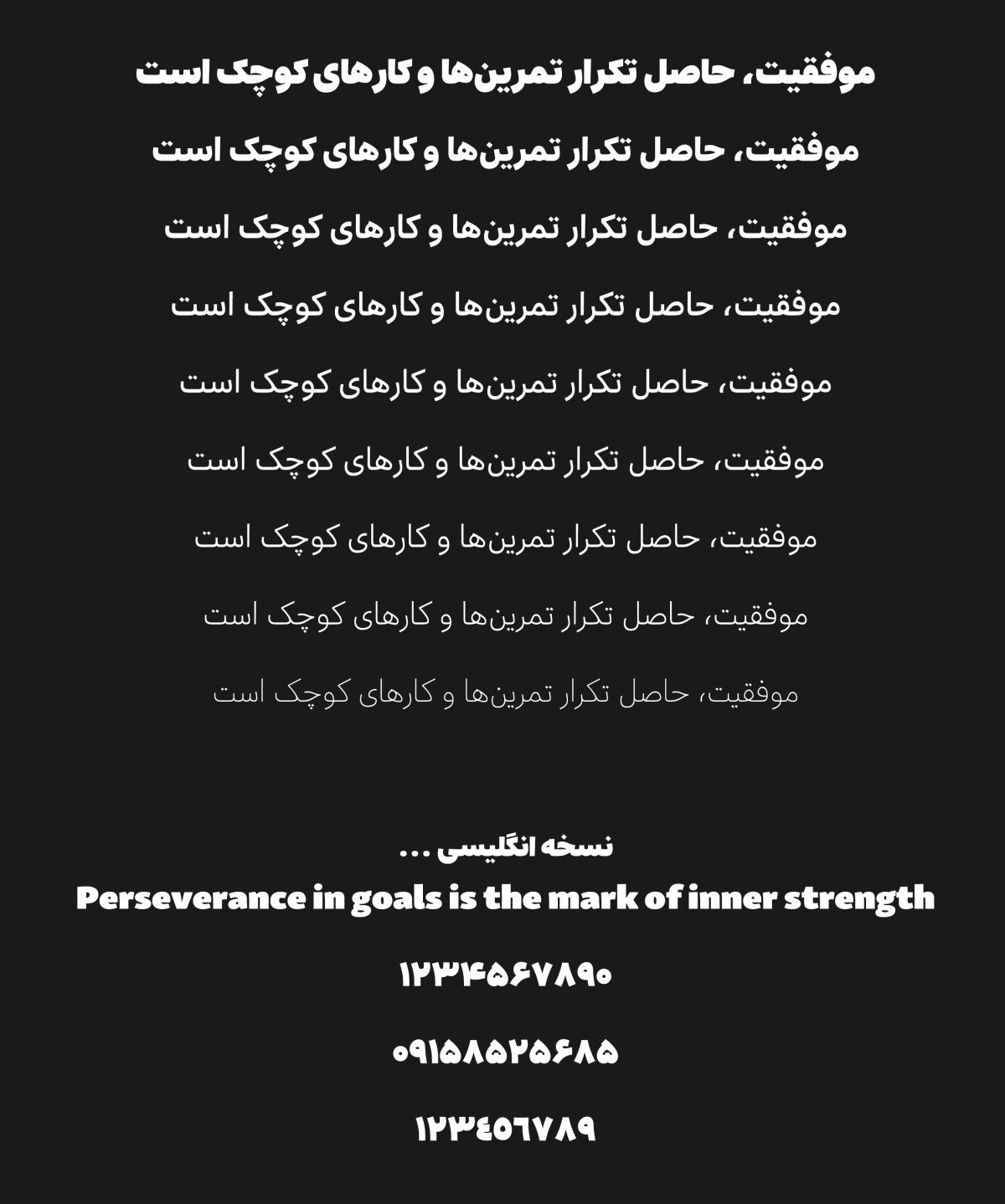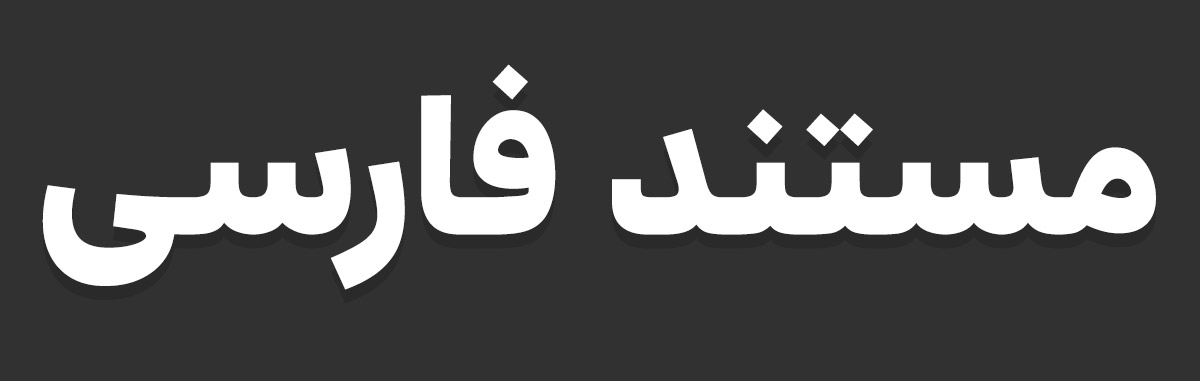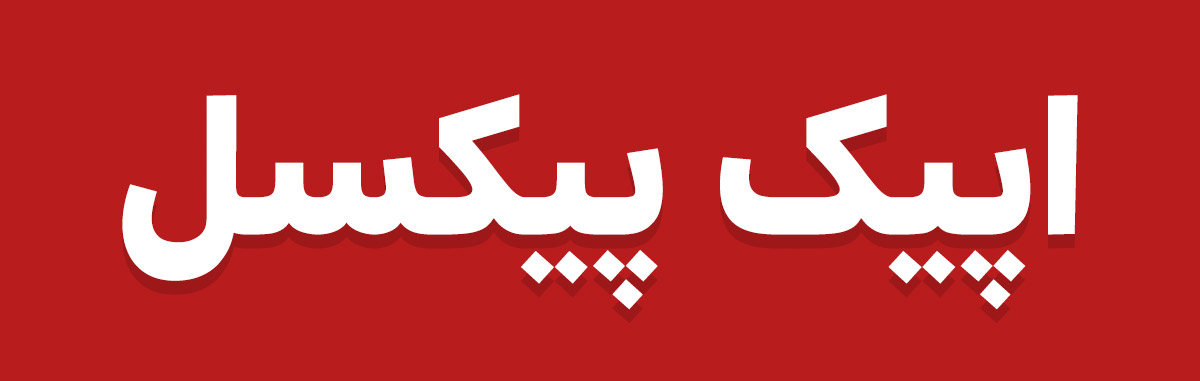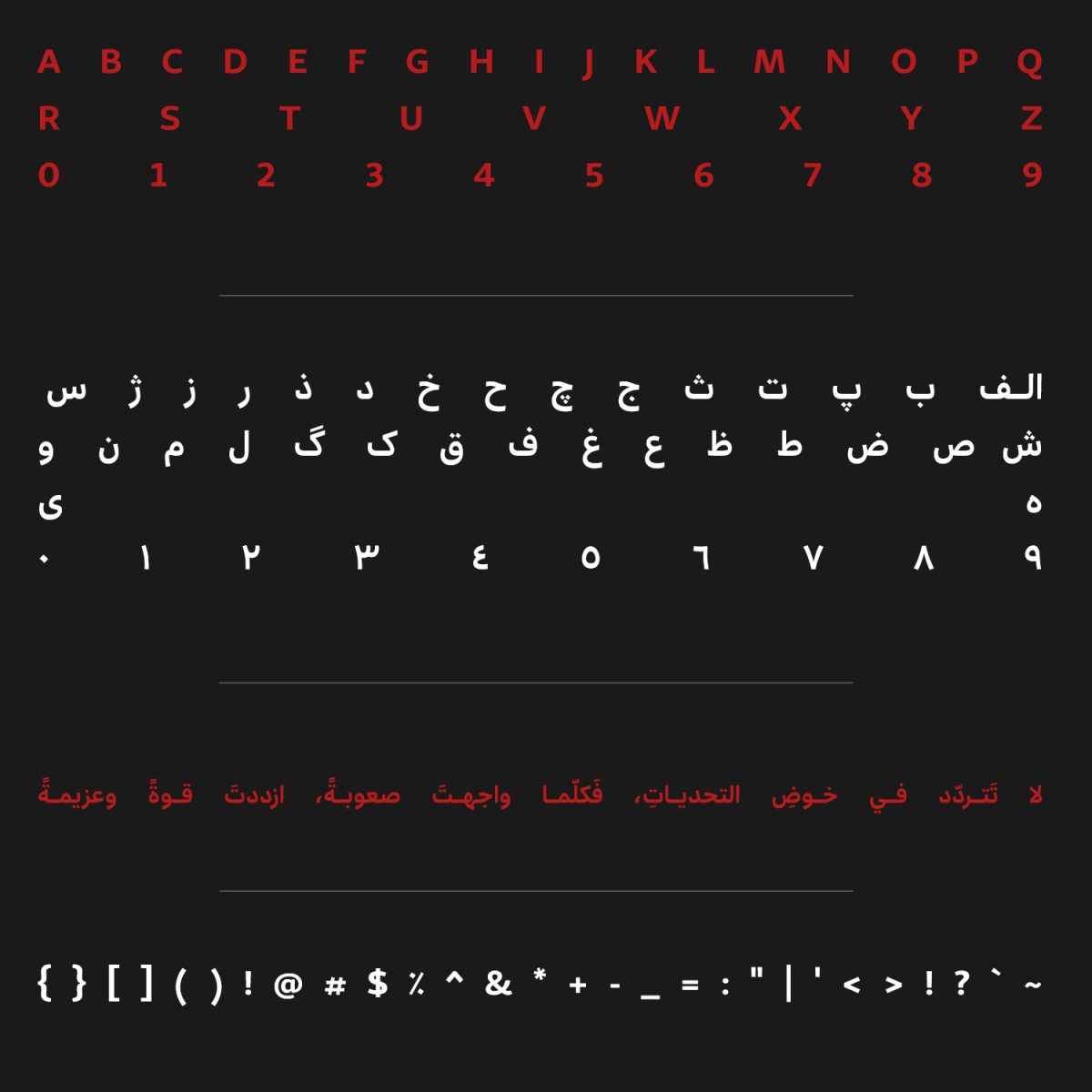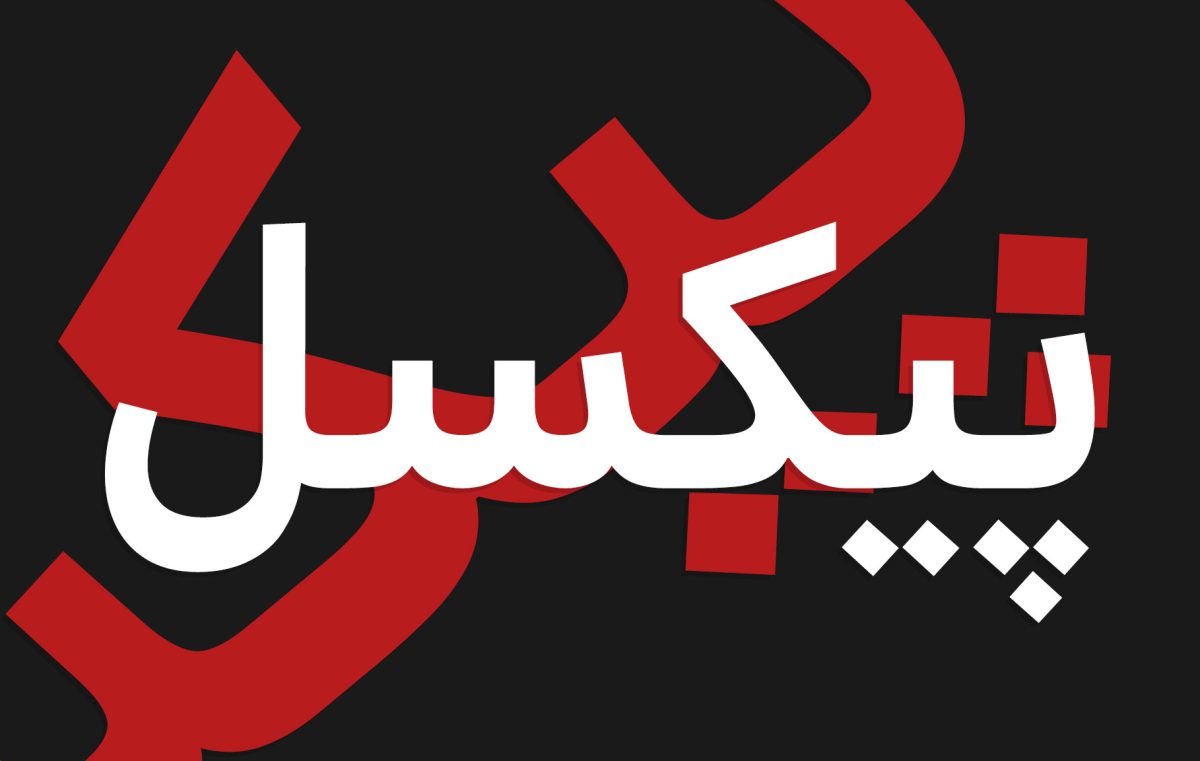
9 فونت مارلیک Marlik
فونت مارلیک فارسی (Marlik)، یک قلم با طراحی هندسی است که بر دقت در جزئیات تأکید دارد. این فونت با شخصیتی نمایشی و جذاب، همراه با حس شادابی و سادگی، برای جلب توجه خواننده ایده آل است. مارلیک به صورت یک فونت متغیر (VF) ارائه می شود و دارای ۹ وزن مختلف است که انعطاف پذیری بالایی در طراحی می دهد. این فونت از زبان های فارسی و انگلیسی پشتیبانی می کند و ویژگی مهم آن، پشتیبانی از اعداد فارسی است. فونت مارلیک که در تاریخ ۱۴۰۲/۶/۱۱ منتشر شده، انتخابی مناسب برای طراحی وب، رابط کاربری، عناوین و انواع طرح های گرافیکی مدرن است.
فونت مارلیک فارسی (Marlik): قلم متغیر با ۹ وزن، طراحی هندسی و پشتیبانی از اعداد فارسی
فونت مارلیک فارسی (Marlik)، قلمی مدرن و کاربردی در دنیای تایپ فیس های دیجیتال است که در دسترس طراحان و توسعه دهندگان قرار گرفته است. این فونت با تمرکز بر طراحی هندسی و دقت در جزئیات خلق شده است و زیبایی ساختارهای منظم هندسی را به نمایش می گذارد.
مارلیک نه تنها از نظر بصری جذاب است، بلکه از نظر فنی نیز قابلیت های پیشرفته ای دارد. این فونت به صورت یک فونت متغیر (Variable Font) عرضه می شود که این تکنولوژی نوین، امکان تنظیم دقیق ضخامت قلم را به صورت پیوسته در نرم افزارها و مرورگرهای پشتیبانی کننده فراهم می کند. علاوه بر این، فونت مارلیک در ۹ وزن مختلف استاندارد نیز ارائه می شود که این تنوع وزن، استفاده از آن را در سطوح مختلف سلسله مراتب بصری (از متن های کوچک تا عناوین بزرگ) ممکن می سازد.
دانلودشخصیت بصری فونت مارلیک را می توان با واژه هایی مانند نمایشی و جذاب توصیف کرد. این فونت در عین حال شاداب و ساده است، و این ترکیب سادگی و جذابیت، آن را برای خواننده دلپذیر و گیرا می سازد. طراحی هندسی و بدنه محکم حروف، به آن حس استحکام و شجاعت می بخشد.
فونت مارلیک یک فونت چندزبانه کاربردی است. این فونت به طور کامل از زبان های فارسی و انگلیسی پشتیبانی می کند. یک ویژگی بسیار کاربردی برای کاربران فارسی زبان، پشتیبانی کامل از اعداد فارسی است؛ به این معنی که اعداد انگلیسی یا عربی ورودی به صورت خودکار با ارقام فارسی نمایش داده می شوند. این فونت در تاریخ ۱۴۰۲/۶/۱۱ (شهریور ۱۴۰۲) منتشر شده است.
کاربردهای فونت مارلیک در طراحی و وب
فونت مارلیک فارسی (Marlik)، با طراحی هندسی، تنوع وزن ها و قابلیت فونت متغیر، برای کاربردهای گسترده ای در طراحی گرافیک، وب و موبایل مناسب است. این فونت ابزاری منعطف و جذاب برای ایجاد جلوه های بصری مدرن است.
این فونت انتخابی عالی برای عناوین اصلی در وبسایت ها، اپلیکیشن ها و انواع محتواهای چاپی مانند پوسترها و تبلیغات است. طراحی هندسی و شخصیت نمایشی آن را برای طراحی لوگو و المان های برندینگ که به دنبال حس مدرن و دقیق هستند، مناسب می سازد. مارلیک به طور ویژه برای رابط های کاربری (UI) وب و موبایل توصیه می شود، زیرا خوانایی خوبی در اندازه ها و وزن های مختلف دارد و قابلیت فونت متغیر در طراحی واکنش گرا بسیار مفید است. می توان از آن در چاپ و نشر نیز برای جلد کتاب و مجلات یا تایپوگرافی های هنری استفاده کرد. پشتیبانی از فارسی و انگلیسی و اعداد فارسی، کاربرد آن را در پروژه های دوزبانه و محتوای فارسی زبان گسترش می دهد. سادگی و جذابیت آن نیز آن را برای استفاده در شبکه های اجتماعی مناسب می سازد.